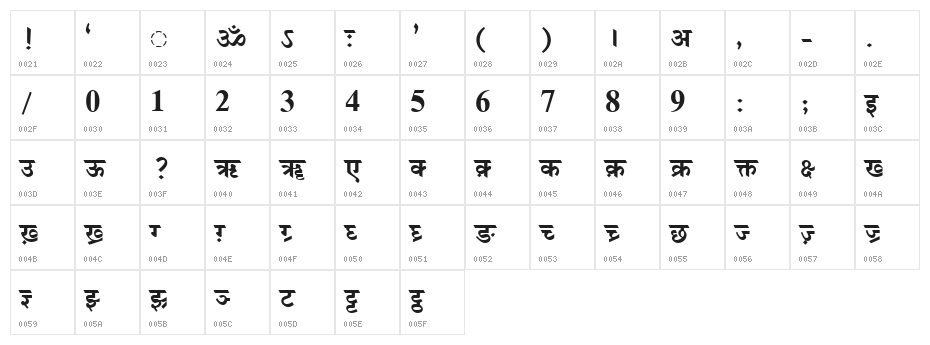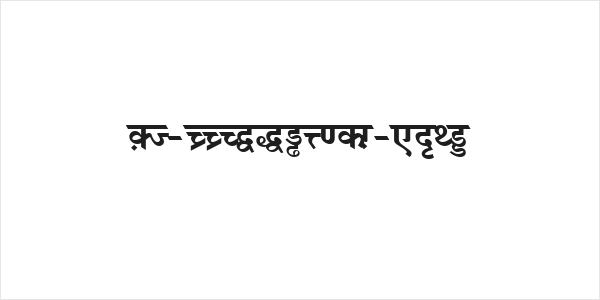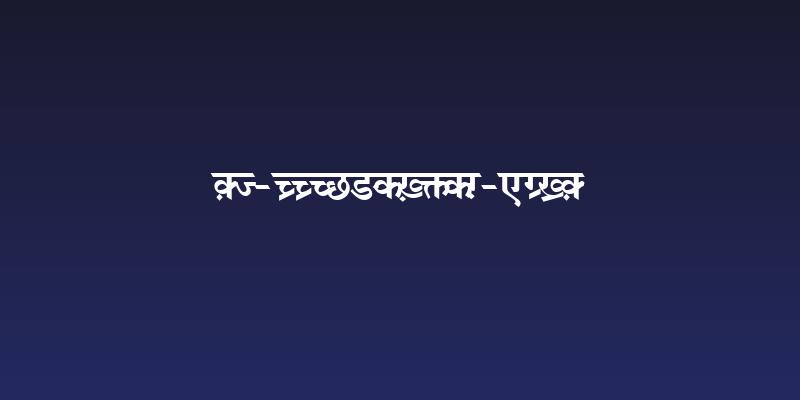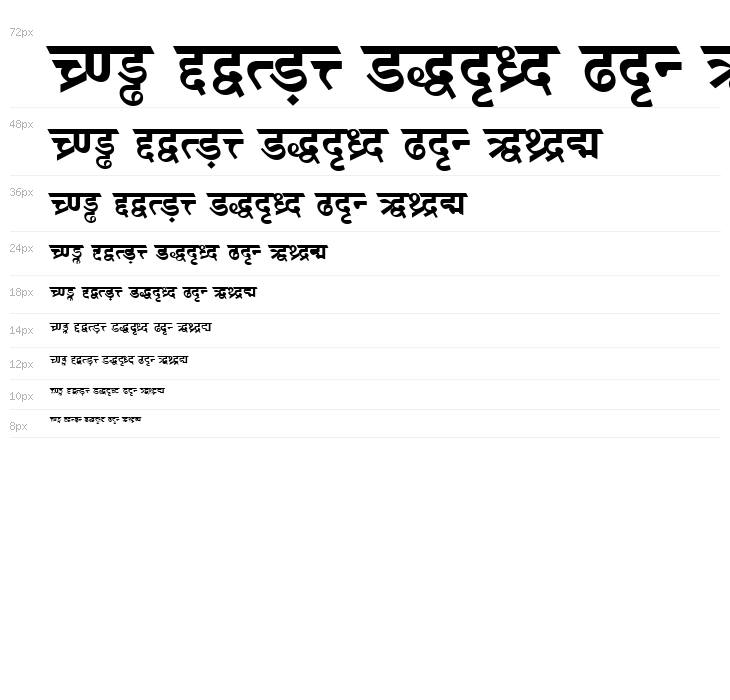
DV-TTSurekhEN-Bold Font
| Gesamtstil | Traditional |
| Anwendungsfall | Headlines, Signage, Formal documents |
| Vorgeschlagene Projekte | Ideal for formal documents, signage, headlines, and any project requiring a strong, traditional aesthetic. |